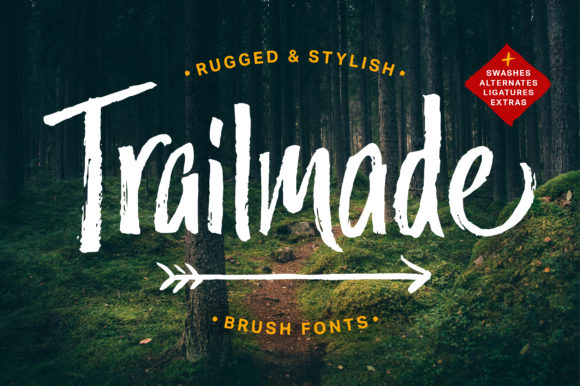
Creativefabrica Trailmade Font
[Creativefabrica] Trailmade Font
Trailmade - это прочный и стильный шрифт кисти. Ручной ввод с помощью пера кисти на бумаге с обычным, курсивным и дополнительным стилем. Исследуйте приключенческий путь с этим шрифтом, который немного выходит за рамки типичного жанра шрифта кисти, но все же несет в себе его отголоски. Прямой дизайн обычного стиля имеет уверенный внешний вид, в то время как курсивный стиль придаёт немного больше фирменного стиля.